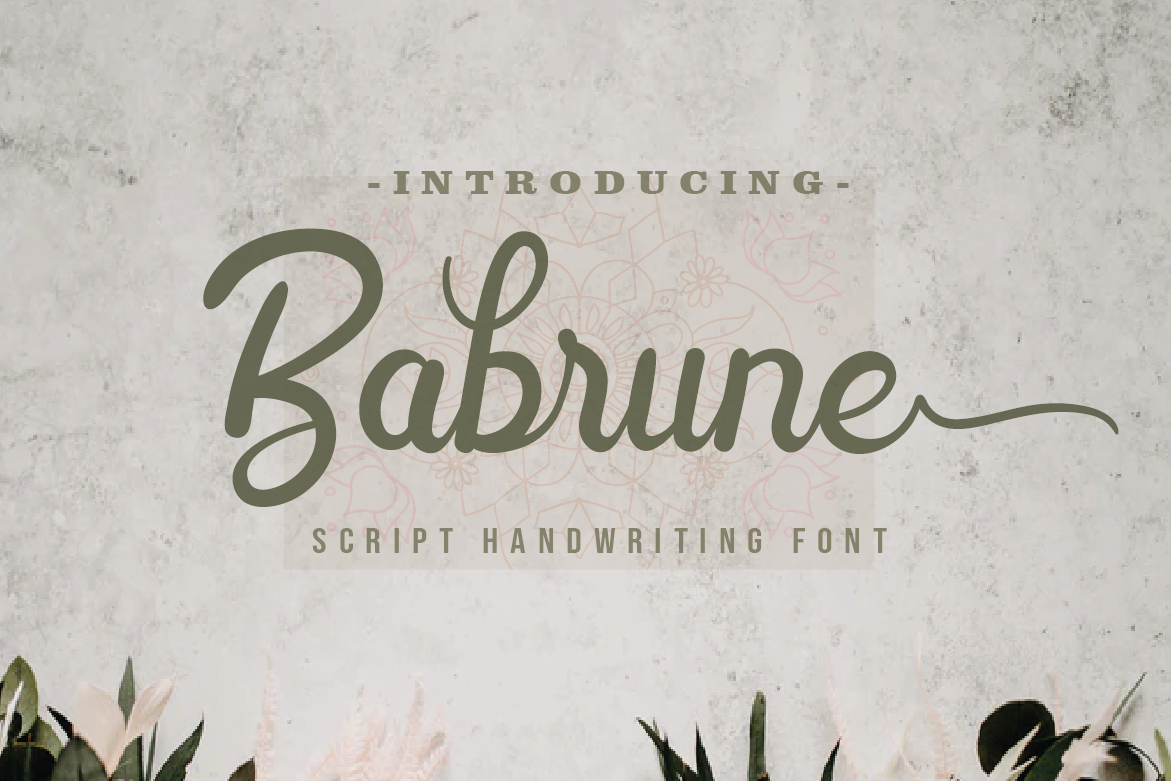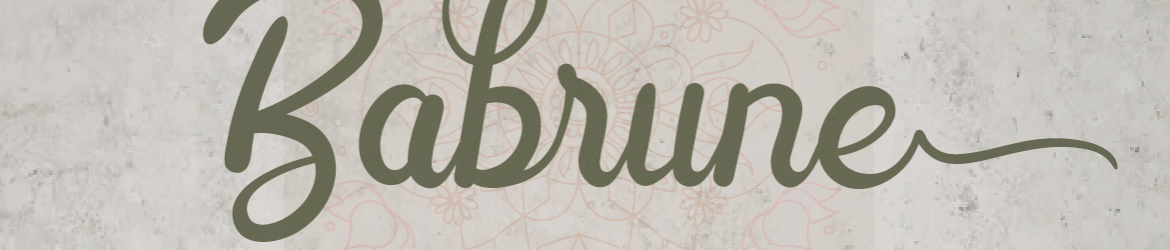
Esta é uma fonte frondesada que transmite beleza e suavidade. Foi criada especialmente para textos formais e românticos como convites de casamento, cartas pessoais, logomarcas ou qualquer outro design que precise de um toque íntimo e único. A Design Amour é o criador desta fonte delicada e elegante, ideal para quando você deseja adicionar uma atmosfera romântica a um design. Seja em um convite de casamento, onde cada palavra carrega um amor sincero e intenso, ou num logotipo de marca, onde a letra frondesada transmite seriedade e confiança ao mesmo tempo. A Design Amour investiu tempo no desenvolvimento desta fonte, focando no aspecto suave das letras que se destacam em sua elegância. Este é um recurso gráfico perfeito para quem busca personalidade sem perder a precisão de seus designs digitais.